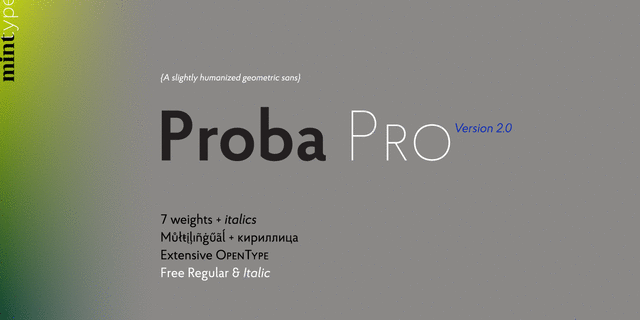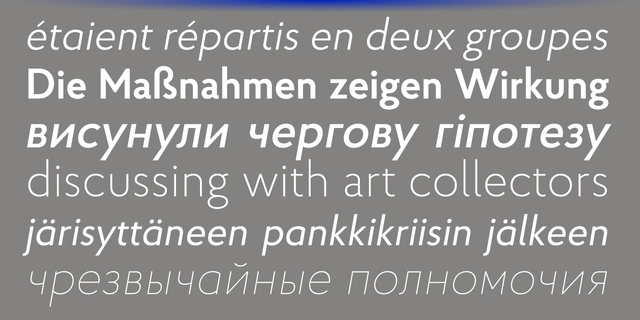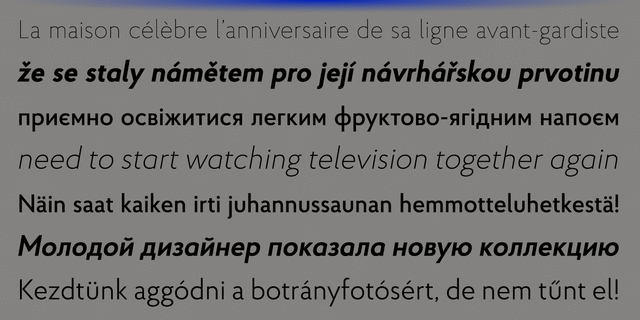
Proba Pro – геометрический гротеск с пониженной высотой строчных, заметными выносными элементами и легким гуманистическим оттенком. Гарнитура содержит 7 вариантов насыщенности + соответствующие курсивные начертания. Каждое начертание поддерживает многочисленные языки, основанные на латинице и кириллице. Шрифт снабжен многими OpenType фичами: лигатуры, капитель, 4 набора цифр, 2 стилистических набора, дроби, нижние и верхние индексы, адаптивную пунктуацию. Также есть языковые альтернативы для румынского, каталонского и тюркских языков. Шрифт Proba Pro разработал и выпустил Андрей Константинов в студии Mint Type в 2014 году.
Ассоциации c семейством Proba ProКачества и характер:
деликатный, чистый, легкий, прохладный, свежий, модный, тонкий, современный, лаконичный, качественный, невесомый, прозрачный, интимный, хрупкий, нежный, воздушный, стеклянный, проволочный, худой, ясный, ровный, понятный, городской, строгий, точный, простой, комфортный, удобный, твердый, мотивирующий, сильный, убедительный